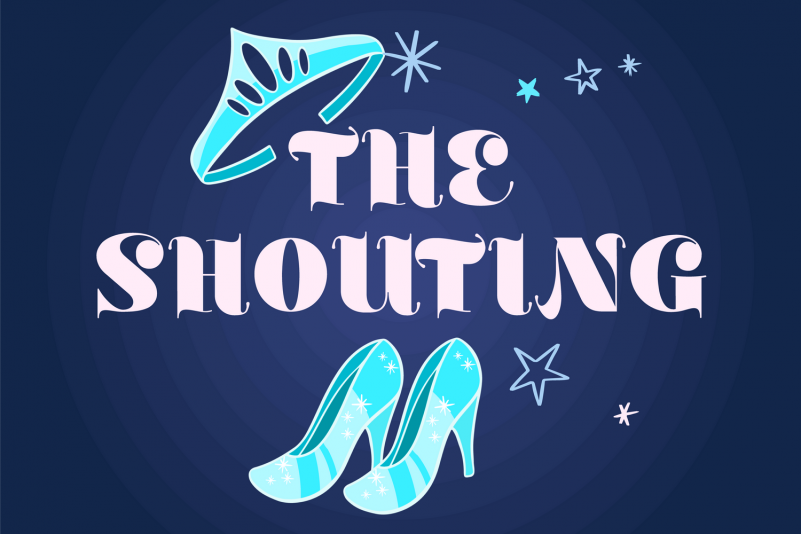
A fonte “The Shouting Font” é uma escolha criativa para qualquer projeto de design que precisa chamar a atenção. Inspirada nos estilos de design dos anos 60, essa fonte bold e divertida traz um tom moderno e vibrante. Ela foi projetada para maximizar seu impacto em logotipos, mas também pode ser usada com sucesso em diversos formatos, desde adesivos de camiseta até anúncios nas redes sociais. Com contrastes muito altos entre as letras, a “The Shouting Font” é um recurso essencial para quem procura uma fonte que traga força e energia ao seu projeto. Sem dúvida, esse é um tipo de font que se destaca, sendo ideal tanto para aplicar em materiais visuais quanto para desempenhar o papel de imagem de design.